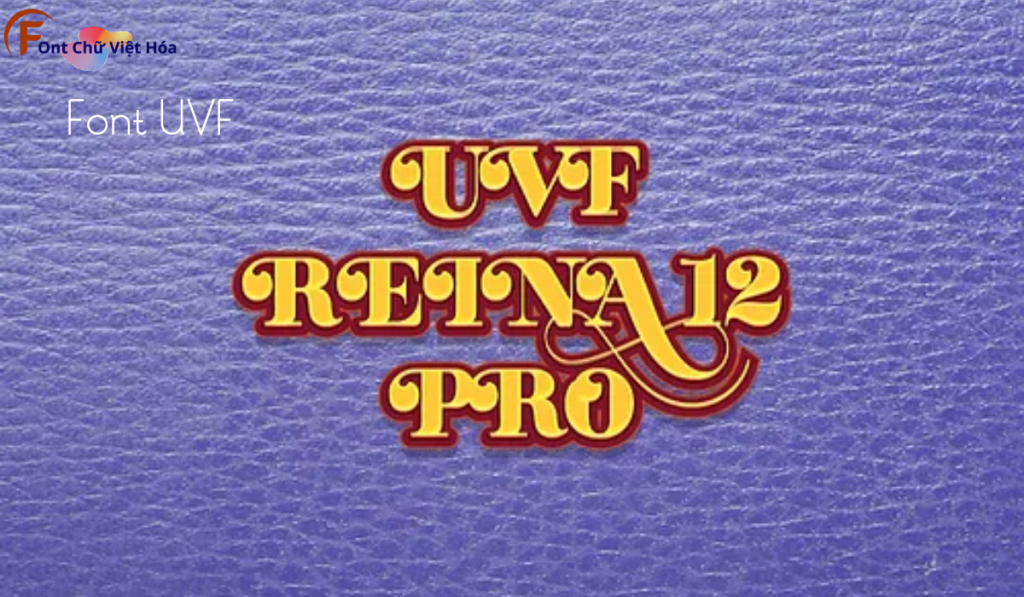
Font UVF Reina 12 Pro Việt Hóa
Độ dày: Regular, Medium, Bold
UVF Reina 12 Pro Việt Hóa là font serif với các đường nét thanh thoát và tinh tế, thuộc bộ font UVF. Font này được thiết kế nhằm mục tiêu tạo ra sự sang trọng và dễ đọc, đặc biệt phù hợp cho các thiết kế như sách, báo, và tài liệu. Đặc điểm hình dạng của UVF Reina 12 Pro là các đường nét rõ ràng và tỷ lệ chữ cân đối, giúp tạo ấn tượng thị giác mạnh mẽ và tối ưu hóa không gian trong thiết kế. Font này cũng đã được Việt hóa, mang đến sự linh hoạt và tiện dụng cho các dự án thiết kế bằng tiếng Việt, giúp người dùng dễ dàng tiếp cận và sử dụng.